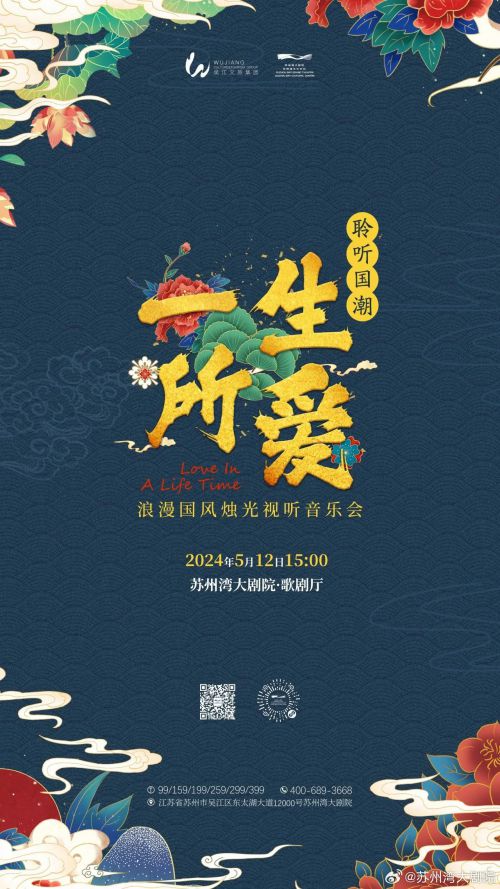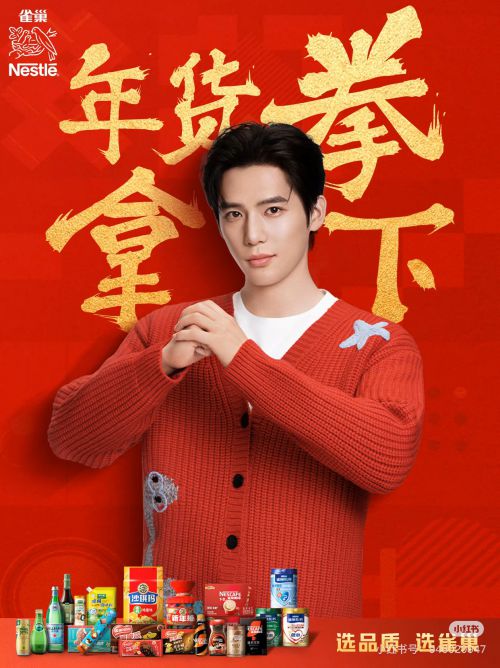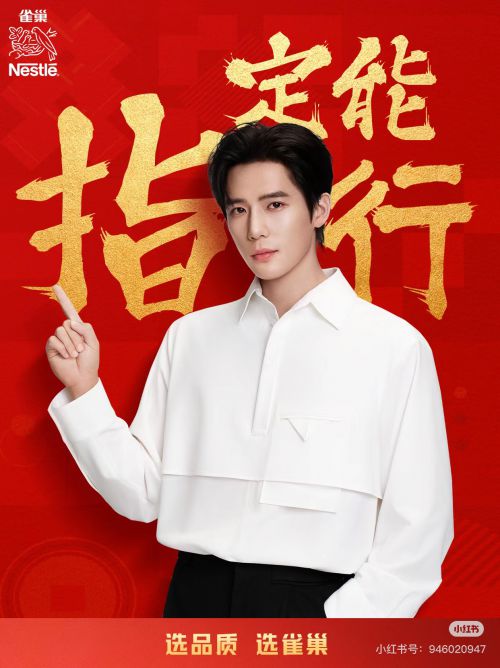
三极泼墨体
字库品牌: 三极字库
三极泼墨体是一款充满中国风韵味的手写体字体,将传统书法的豪放气势与现代设计需求巧妙融合。作为三极字库旗下的免费商用字体,其粗字重设计赋予作品强烈的视觉冲击力,是表达力量感与文化底蕴的理想选择。 三极泼墨体字形方正稳健,重心居中,中宫宽博的结构设计,既保留了手写字体的灵动性,又展现出沉稳大气的视觉张力。字体笔画融入传统泼墨艺术的写意感,毛笔笔触特征鲜明,通过自然的粗细变化与墨色晕染效果,生动还原了毛笔书写时的笔锋转折与飞白质感。 三极泼墨体整体笔画偏粗,通过强烈的粗细对比强化了字体的力量感与豪放气质,笔画间自然衔接的连贯性更增添了书写的韵律美。无论是中国风设计、文化主题创作还是手写风格标题,都能传递出洒脱不羁的艺术张力,为海报、包装、广告等场景注入独特的东方美学魅力。